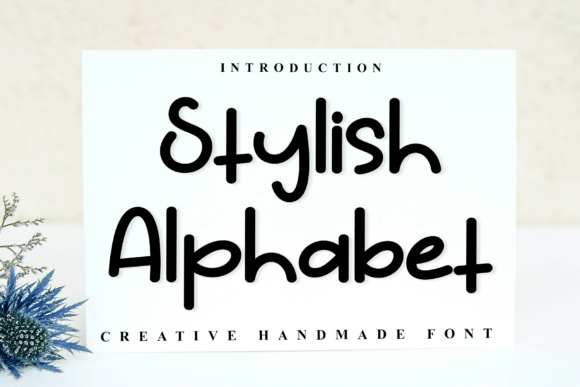
Stylish Alphabet
Stylish Alphabet: A Fonte Handmade que Transforma Seu Projeto
Se você procura uma tipografia que una personalidade e versatilidade, a Stylish Alphabet é a escolha certa. Desenvolvida de forma artesanal, ela traz um visual contemporâneo que destaca qualquer peça criativa, seja um convite elegante ou um cartaz divertido para crianças.
- Design único e brincalhão – Cada letra possui “saltos” e curvas que dão vida ao texto, fazendo com que as palavras literalmente “saltem” da página.
- Traços ousados e fluidos – A espessura marcante garante ótima legibilidade, enquanto as linhas suaves mantêm a elegância.
- Aplicações perfeitas – Ideal para cartões de felicitações, convites, branding infantil, logos cativantes e posters que precisam de um toque de “cool”.
- Combinação inteligente – Para um layout profissional de alto contraste, combine a Stylish Alphabet com uma fonte monoline fina (ex.: Montserrat Light ou Open Sans Regular).
Ao escolher a Stylish Alphabet, você garante que seu projeto se destaque em meio a fontes genéricas. Experimente usar cores vibrantes ou texturas sutis para potencializar ainda mais o efeito visual. O resultado? Uma peça que transmite criatividade, energia e profissionalismo ao mesmo tempo.